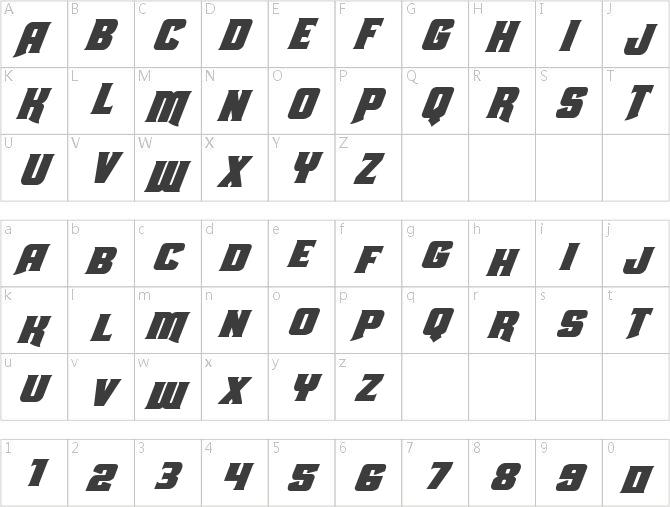
Union Gray Super-Italic 詳情頁
Union Gray Super-Italic
Union Gray Super-Italic字體字庫是一款讓人賞心悅目、百看不厭的英文字體,適合各類廣告和產(chǎn)品包裝設(shè)計(jì)應(yīng)用,字體大小0.04MB,格式為ttf字體,上傳用戶是得·岸,作者/版權(quán)方為未知